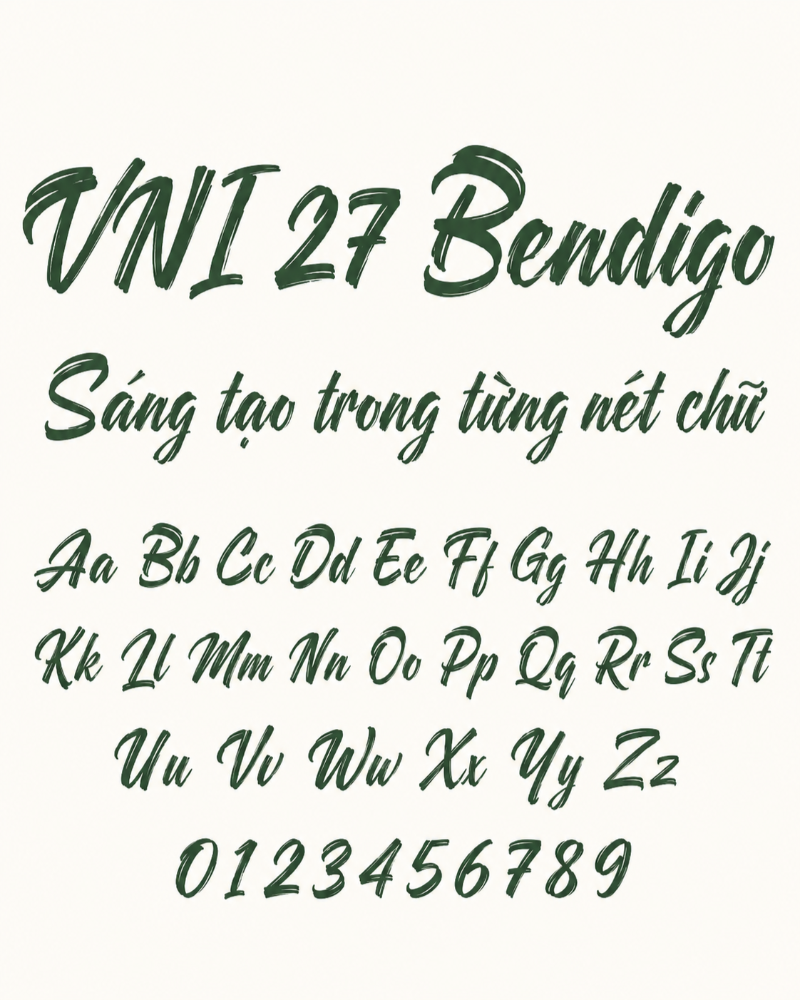
Những nét chữ thư pháp mềm mại, uyển chuyển luôn có sức hấp dẫn riêng trong thiết kế, nhất là khi các giá trị văn hóa Á Đông ngày càng được khai thác mạnh mẽ trong mỹ thuật hiện đại. Sự kết hợp giữa tinh thần thư pháp truyền thống, nét bút lông phóng khoáng của ông Đồ và công nghệ font chữ kỹ thuật số đã mở ra một kho tài nguyên giàu cảm hứng cho designer. Trong bài viết này, In Đại Minh sẽ giới thiệu cho bạn 9+ font chữ thư pháp Việt hóa đẹp, dễ ứng dụng, cùng với cách chọn và sử dụng font sao cho tinh tế, sang trọng, tránh cảm giác rườm rà, lỗi thời hoặc quá “sến” trong thiết kế.
Font chữ thư pháp là gì và nên dùng trong trường hợp nào?
Font chữ thư pháp, hay còn gọi là Calligraphy Fonts, là nhóm phông chữ được tạo ra để tái hiện vẻ đẹp của nét bút lông, nét cọ hoặc chữ viết tay nghệ thuật. Điểm đặc trưng của kiểu font này nằm ở sự mềm mại, bay bổng và khả năng chuyển đổi linh hoạt giữa nét thanh – nét đậm. Nhờ đó, font thư pháp luôn mang lại cảm giác thủ công, giàu tính nghệ thuật và đậm chất truyền thống.
Vậy khi nào nên sử dụng font chữ thư pháp?
Kiểu chữ này phát huy hiệu quả tốt nhất trong những thiết kế cần sự trang trọng, tinh tế hoặc mang hơi thở văn hóa. Cụ thể, font thư pháp rất phù hợp để dùng trong:
- Thiết kế thiệp cưới, thiệp chúc Tết, bao lì xì.
- Trình bày câu đối, tranh chữ, bình phong trang trí.
- Thiết kế bìa sách văn học, sách lịch sử hoặc album nhạc truyền thống.
- Làm poster cho các sự kiện văn hóa, lễ hội, chương trình nghệ thuật.
- Thiết kế bao bì sản phẩm mang màu sắc cổ truyền như trà, mứt, gốm sứ, đông y.
- Sáng tạo logo phong thủy hoặc logo cho thương hiệu muốn nhấn mạnh yếu tố thủ công, bản sắc và giá trị di sản.
Top 9+ font chữ thư pháp đẹp, đáng dùng cho thiết kế
Để bạn dễ chọn được font chữ phù hợp với phong cách thiết kế, dưới đây chúng tôi xin chia sẻ những font chữ thư pháp đẹp được chọn lọc từ nhiều nguồn khác nhau:
Font UTM Ông Đồ Già
UTM Ông Đồ Già được xem là một trong những font thư pháp Việt quen thuộc và được sử dụng nhiều nhất. Nét chữ có độ xước nhẹ, gợi cảm giác như được viết bằng cây cọ đã vơi mực. Tổng thể font mang vẻ cứng cáp, cổ kính và đậm dấu ấn thời gian. Đây là lựa chọn rất phù hợp để thiết kế câu đối Tết, tranh chữ thư pháp hoặc các ấn phẩm mang phong cách truyền thống.
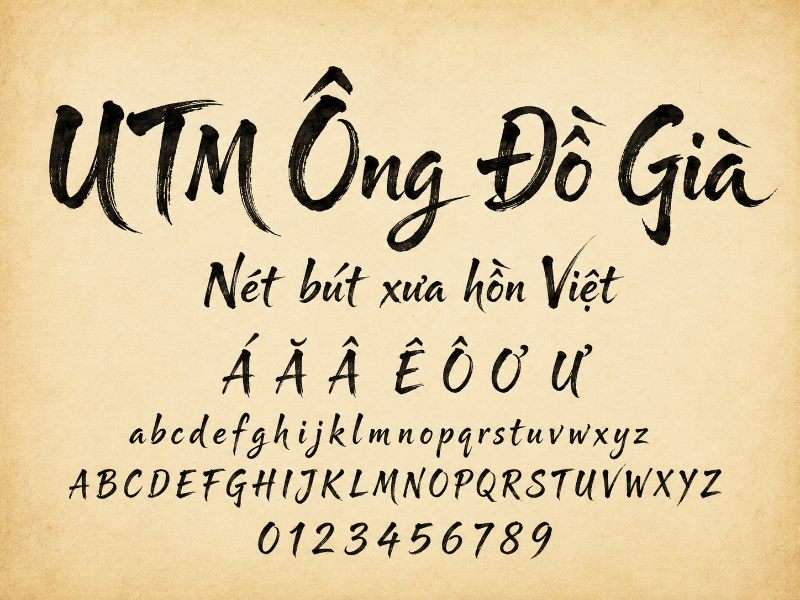
Font UTM Ông Đồ Trẻ
Nếu UTM Ông Đồ Già tạo cảm giác trầm mặc và hoài cổ, thì UTM Ông Đồ Trẻ lại mang tinh thần nhẹ nhàng, mềm mại và sáng hơn. Các nét chữ thanh thoát, uyển chuyển nhưng vẫn giữ được chất thư pháp Việt. Font này phù hợp với những thiết kế cần yếu tố truyền thống nhưng không quá nặng nề, ví dụ như thiệp chúc Tết, thiệp mời, banner văn hóa hoặc ấn phẩm trang trí.
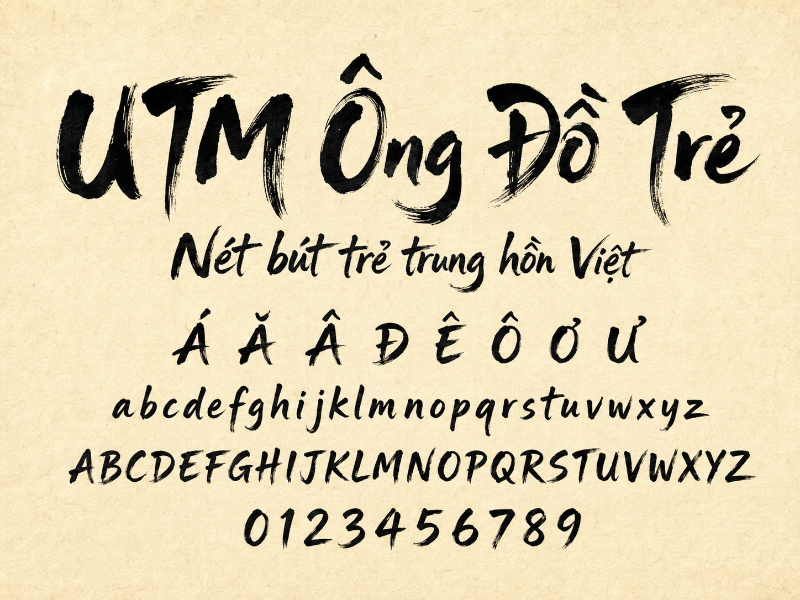
Font VN Opulent Brush
VN Opulent Brush là kiểu font kết hợp hài hòa giữa sự mềm mại của nét cọ và vẻ trang trọng của chữ thư pháp. Các đường nét được xử lý uyển chuyển, tạo cảm giác như từng con chữ được viết trực tiếp bằng bút lông trên giấy. Nhờ vẻ đẹp tinh tế và có chiều sâu, font này rất thích hợp cho các thiết kế tranh chữ, poster nghệ thuật, bìa sách hoặc sản phẩm cần nhấn mạnh tính thủ công và giá trị văn hóa.
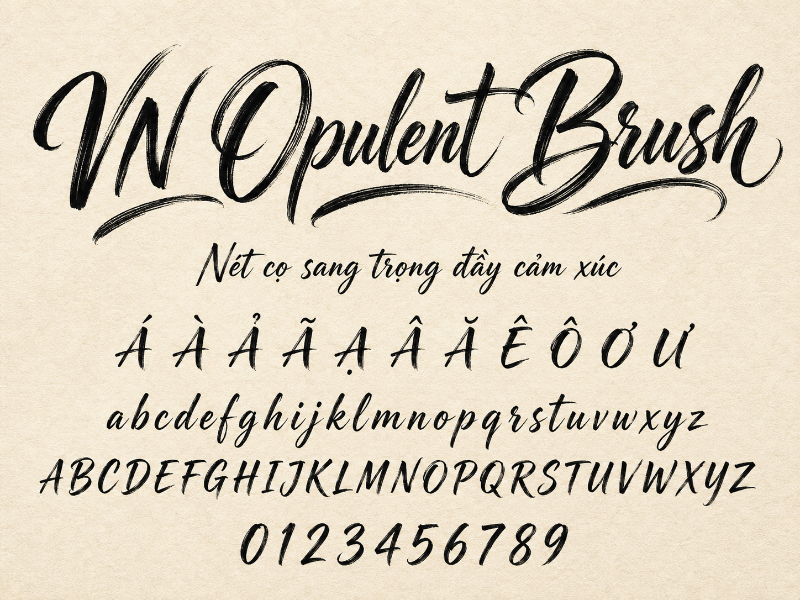
Font VN Lovelista
VN Lovelista gây ấn tượng với nét chữ thanh mảnh, mềm mại và uốn lượn đầy duyên dáng. Kiểu font này mang cảm giác nhẹ nhàng, bay bổng và có phần lãng mạn. Đây là lựa chọn rất phù hợp cho thiệp cưới cao cấp, thiệp mời sự kiện, typography tình yêu hoặc các thiết kế cần thể hiện sự tinh tế, cảm xúc.
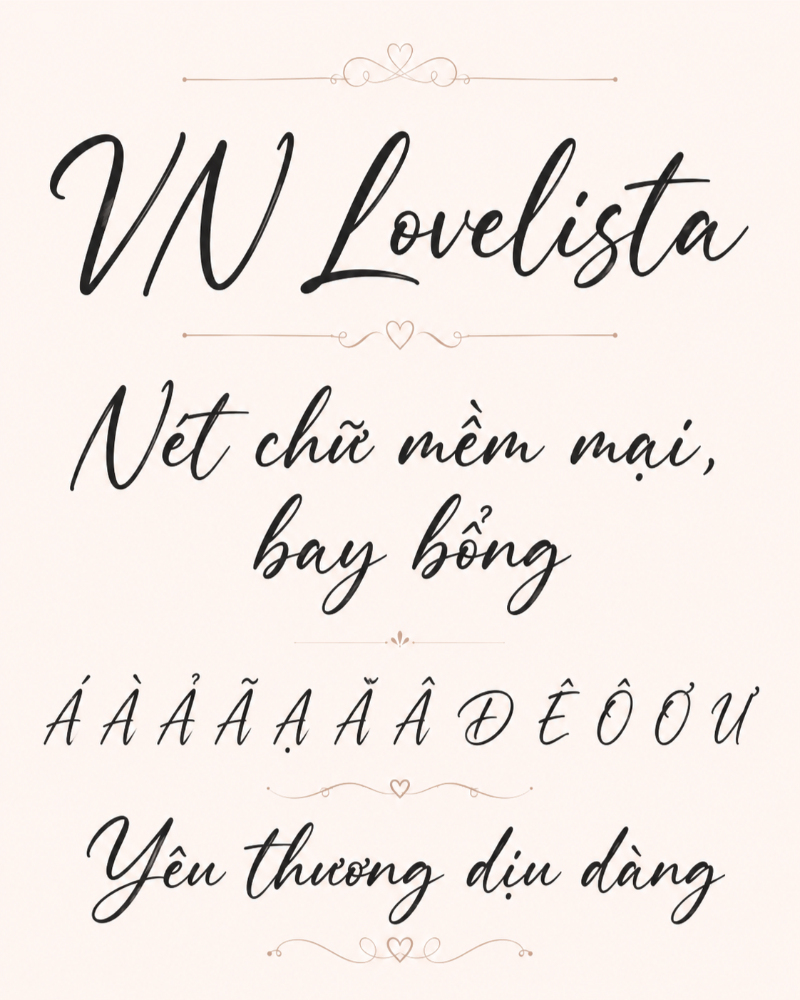
Font MTD Geza Script
MTD Geza Script là sự kết hợp hài hòa giữa phong cách chữ viết tay tự nhiên và những nét nhấn đặc trưng của bút lông. Font không quá cầu kỳ nhưng vẫn đủ mềm mại để tạo điểm nhấn thẩm mỹ. Ưu điểm nổi bật của MTD Geza Script là khả năng hiển thị rõ ràng, dễ đọc ngay cả khi dùng ở kích thước nhỏ. Vì vậy, font này phù hợp cho thiệp, tiêu đề phụ, quote ngắn hoặc các thiết kế cần sự thanh lịch nhưng vẫn đảm bảo tính ứng dụng.
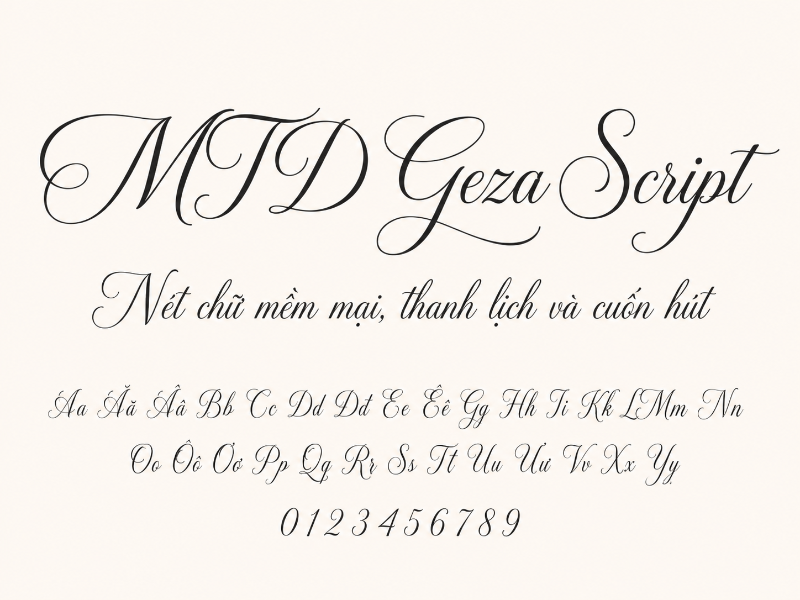
Font Smooch
Smooch sở hữu nét chữ lả lướt, phóng khoáng và giàu tính biểu cảm. Font mang hơi thở của nghệ thuật Calligraphy phương Tây, đồng thời vẫn có chút mềm mại gần với tinh thần Á Đông. Nhờ vẻ đẹp uyển chuyển và cảm giác tự do trong từng nét chữ, Smooch rất thích hợp cho thiết kế thiệp, poster nghệ thuật, tiêu đề trang trí hoặc các ấn phẩm mang phong cách lãng mạn, cá tính.
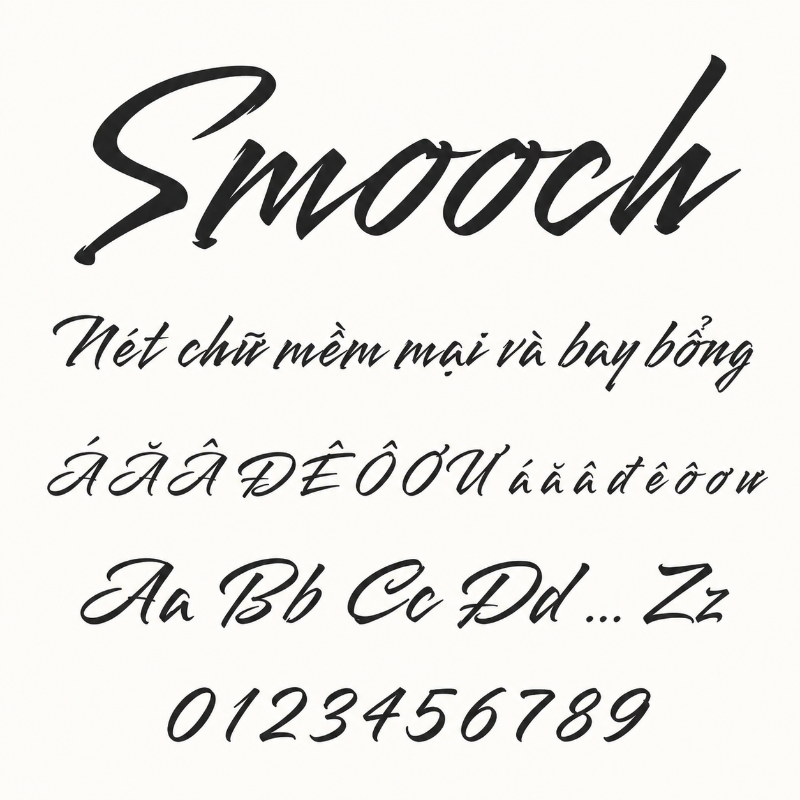
Font LNTH Watermark
LNTH Watermark mang vẻ đẹp thanh thoát, nhẹ nhàng và có chiều sâu tĩnh lặng. Các nét chữ không quá phô trương nhưng tạo được cảm giác trang nghiêm, an nhiên. Đây là lựa chọn rất phù hợp cho những thiết kế liên quan đến Phật giáo, bìa sách thiền, ấn phẩm tâm linh hoặc các nội dung cần truyền tải sự bình yên và sâu lắng.
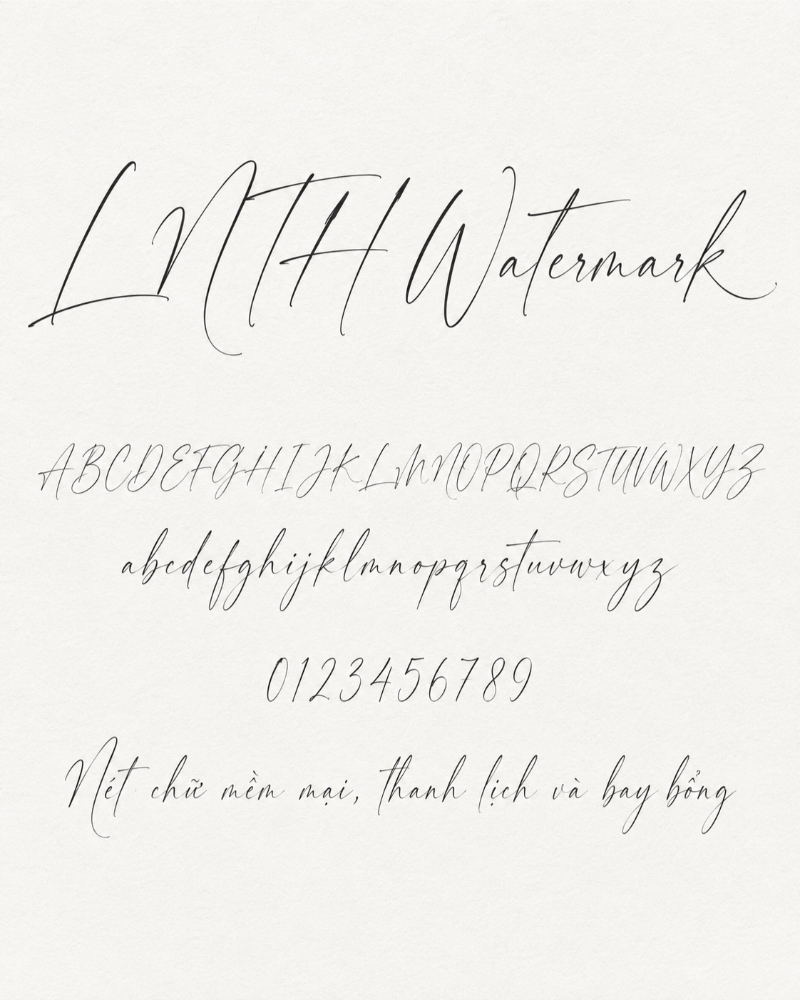
Font Thư Pháp Thiên Ân
Font Thư Pháp Thiên Ân nổi bật với các đường nét sắc sảo, rõ ràng và có độ tương phản mạnh giữa nét thanh và nét đậm. Tổng thể font tạo cảm giác gọn gàng, chắc chắn nhưng vẫn giữ được sự mềm mại đặc trưng của chữ thư pháp. Kiểu chữ này phù hợp với tranh chữ, câu đối, ấn phẩm văn hóa hoặc các thiết kế cần sự an yên, trang trọng và vững chãi.